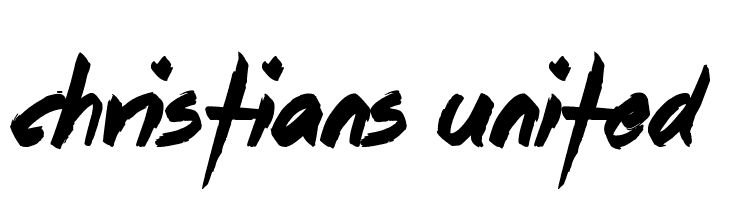
( Fonts by Sam Wang )
A modern, elongated font with thin, elegant lines and a sophisticated appearance.
( Fonts by twinletter )
A bold, playful font with rounded, bubble-like characters for a fun, modern look.
( Fonts by Gassstype )
A bold, playful font with a hand-drawn, retro vibe.
( Fonts by Kayla George )
A whimsical, decorative font with flowing, hand-drawn lines.
( Fonts by Kreative Korporation - www.kreativekorp.com )
A pixelated, retro-style font with a blocky, digital appearance.
( @angrydubs )
A sharp, angular font with a modern, edgy style.
( Fonts by Sharkshock )
A futuristic, geometric font with bold lines and sharp angles.
A bold, textured font with a rugged, distressed appearance.
( Fonts by Billy Argel )
A playful decorative font with heart motifs, perfect for romantic and whimsical designs.
A bold, playful font with exaggerated curves and a quirky style.
( Hendra Pratama )
An elegant, flowing script font with smooth, continuous strokes.
( Fonts by Rodrigo Fuenzalida )
A bold, rounded typeface with a playful and robust appearance.
A bold, cursive script font with a modern, handwritten style.
( Zetafonts - www.zetafonts.com )
A bold, freehand block letter font with a casual, artistic style.
( Fonts by www.aenigmafonts.com )
A bold, playful font with thick, rounded strokes and a bubbly appearance.
A bold, 3D outlined font with a retro, impactful style.
( Sronstudio - Yusron Billah )
A graceful and sophisticated script font with flowing, interconnected letters.
( Fonts by The Scriptorium - Dave Nalle )
A bold, gothic-inspired font with sharp, angular edges and dramatic flourishes.
A bold, modern font with strong, confident letterforms and excellent readability.
( گالری فانت فارسی پژوهش آريانا - only compatible with Farsi and Arabic )
Not a valid Latin font; only numerals and symbols are visible in a calligraphic style.